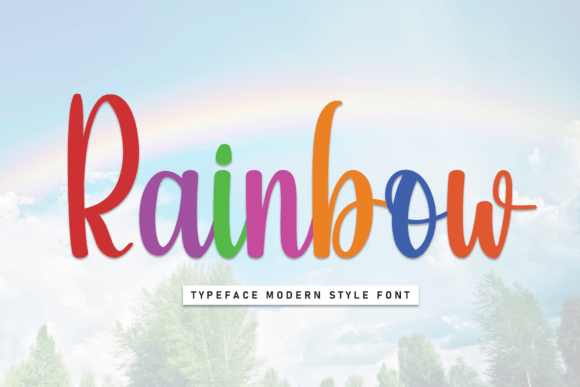
Rainbow Font
Rainbow Font – ألوان الإبداع في كل حرف! ????✨
اجعل تصميماتك تنبض بالحياة مع Rainbow Font، الخط الفريد الذي يمزج بين الألوان الزاهية والأسلوب العصري ليمنح مشاريعك لمسة مميزة واستثنائية.
✅ مثالي لـ:
• تصاميم العلامات التجارية والشعارات
• البوستات الإبداعية على مواقع التواصل الاجتماعي
• الدعوات والبطاقات الرقمية
• مشاريع الطباعة والمنتجات الرقمية
???? مميزاته:
• ألوان متدرجة جذابة تضيف طابعًا حيويًا
✨ ارتقِ بتصميماتك وأضف لمسة من البهجة مع Rainbow Font!